3D-typografie: speel met kleur en volume
Over het eindproject van de cursus: 3D-typografie: speel met kleur en volume
3D-typografie: spelen met kleur en volume
“We zijn aan het einde van de cursus gekomen! Hopelijk was het een zeer nuttige en informatieve ervaring en ik kijk er naar uit om te zien hoe je alles wat je hebt geleerd in je eigen werk opneemt. Nu is het tijd om je eigen stuk te maken. Voor het uiteindelijke project, voel je niet beperkt of onder druk gezet om alleen de C4D-vaardigheden te gebruiken die we in de cursus hebben geleerd. Combineer ze gerust met andere technieken. Probeer creatief te zijn. Deel je compositie stap voor stap en gebruik screenshots om het proces te illustreren. Laten we de belangrijkste stappen bekijken die u voor uw project moet nemen: Doe eerst inspiratie op en maak een ruwe lay-out van de compositie in Adobe Illustrator.
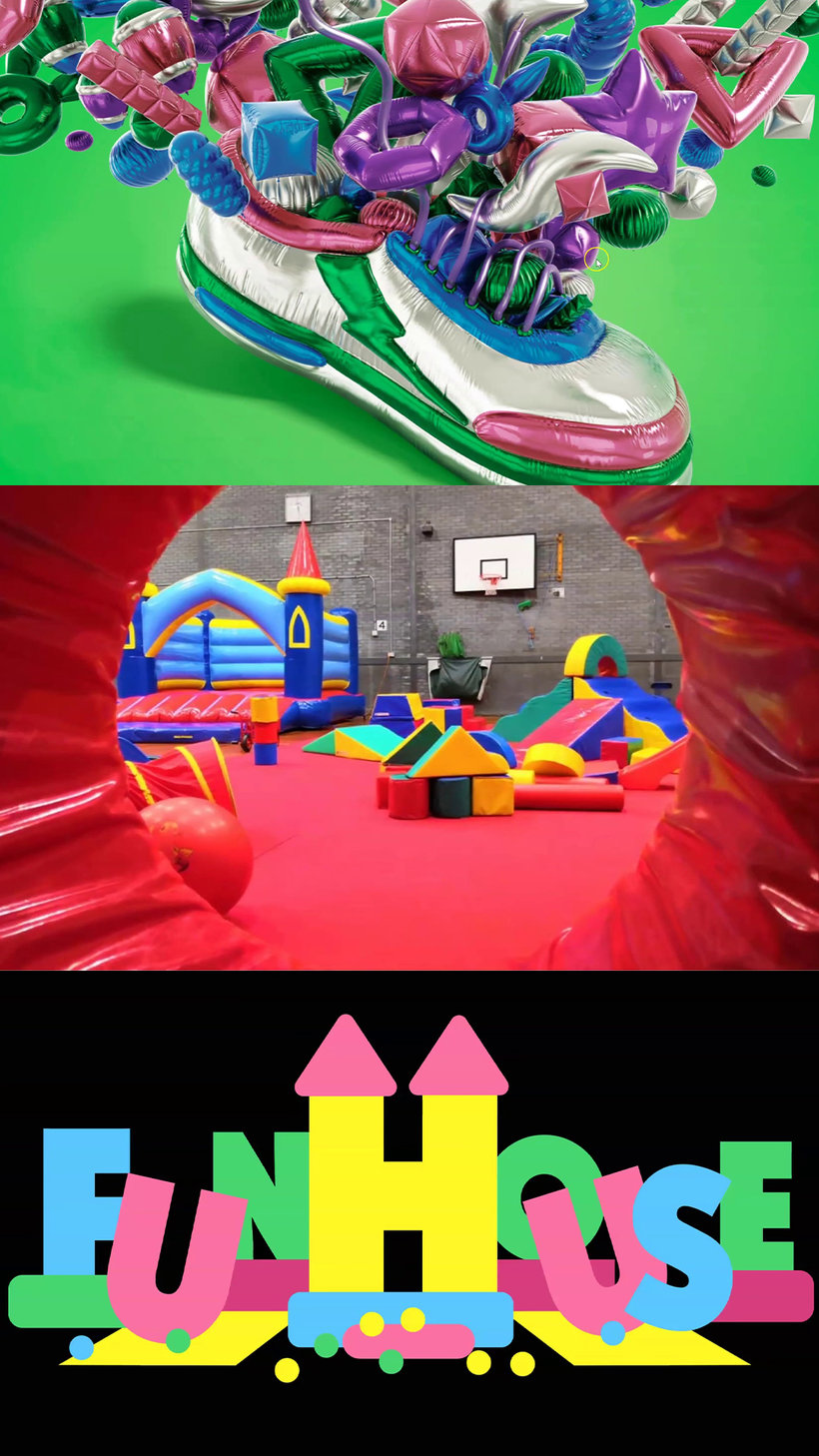
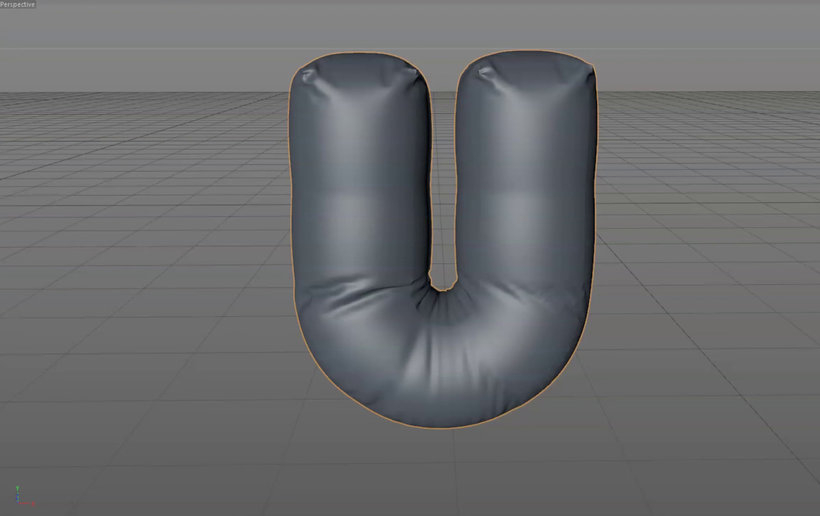
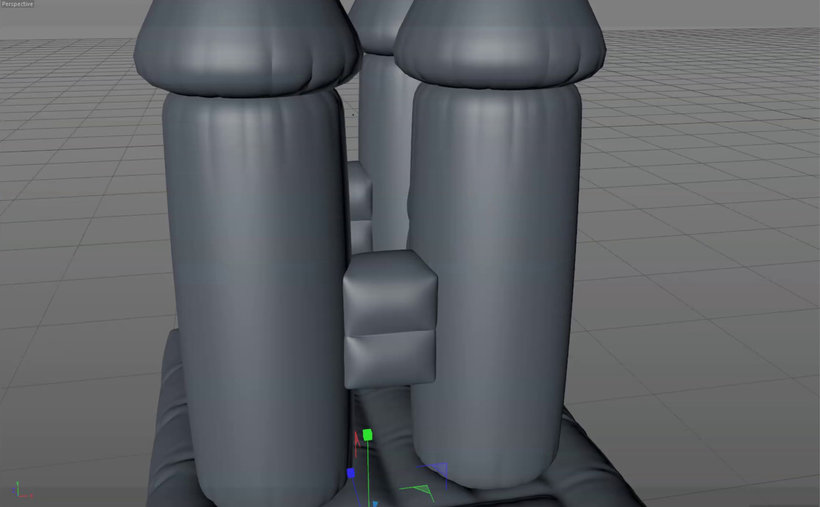
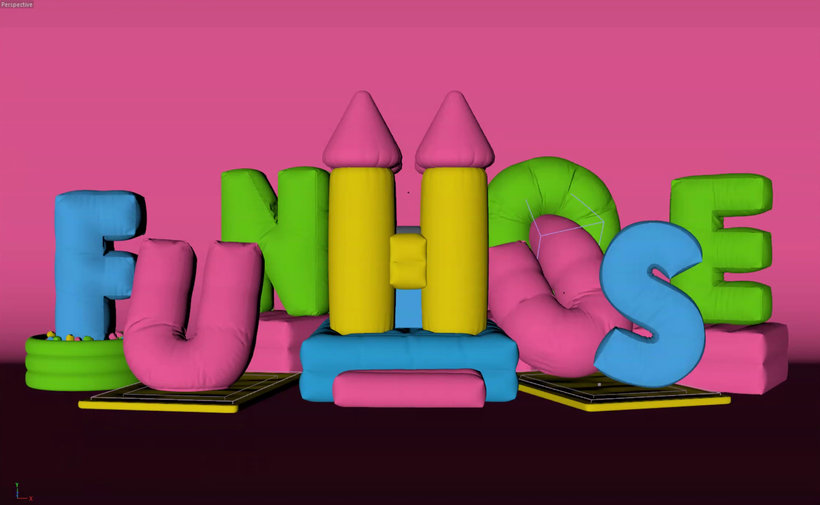
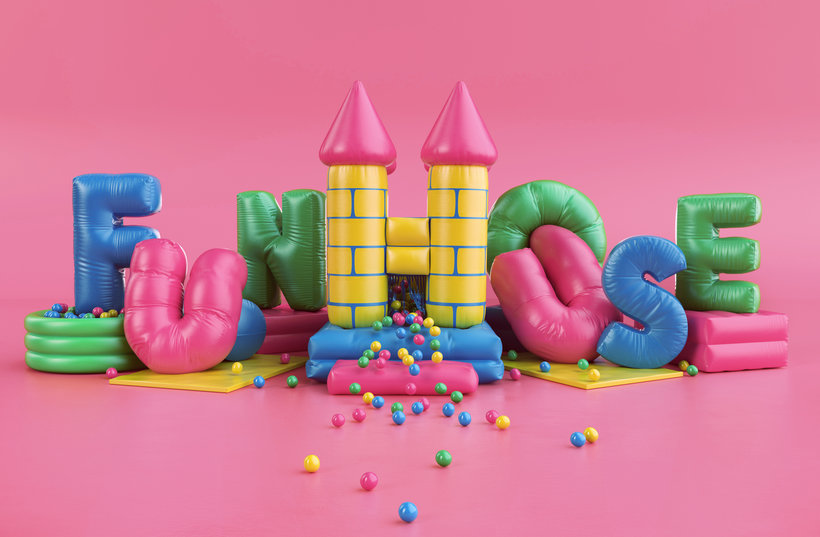
“Laatste project Gefeliciteerd, goed gedaan en bedankt voor het voltooien van deze cursus bij mij. Het is nu tijd om ons eindproject te bespreken. Hopelijk heb je over mij en mijn invloeden geleerd, hoe ik eerste ideeën en concepten genereer, hoe ik dingen schets in 2D in Illustrator en hoe ik alles modelleer en bouw in Cinema 4D, renderen in Roodverschuiving, en ten slotte alles in Photoshop samen te stellen en te bewerken. Ik hoop dat de cursus leuk en informatief was. Voor het laatste project zou ik graag willen dat je eropuit gaat om te creëren je eigen 3D, opblaasbaar typografisch stuk....”
Thomas Burden is een 3D-illustrator uit Chichester, VK. Hij is vooral bekend om zijn unieke visuele stijl die 3D-type en constructies combineert, een esthetiek die is beïnvloed door het speelgoed dat hij als kind nooit mocht hebben.